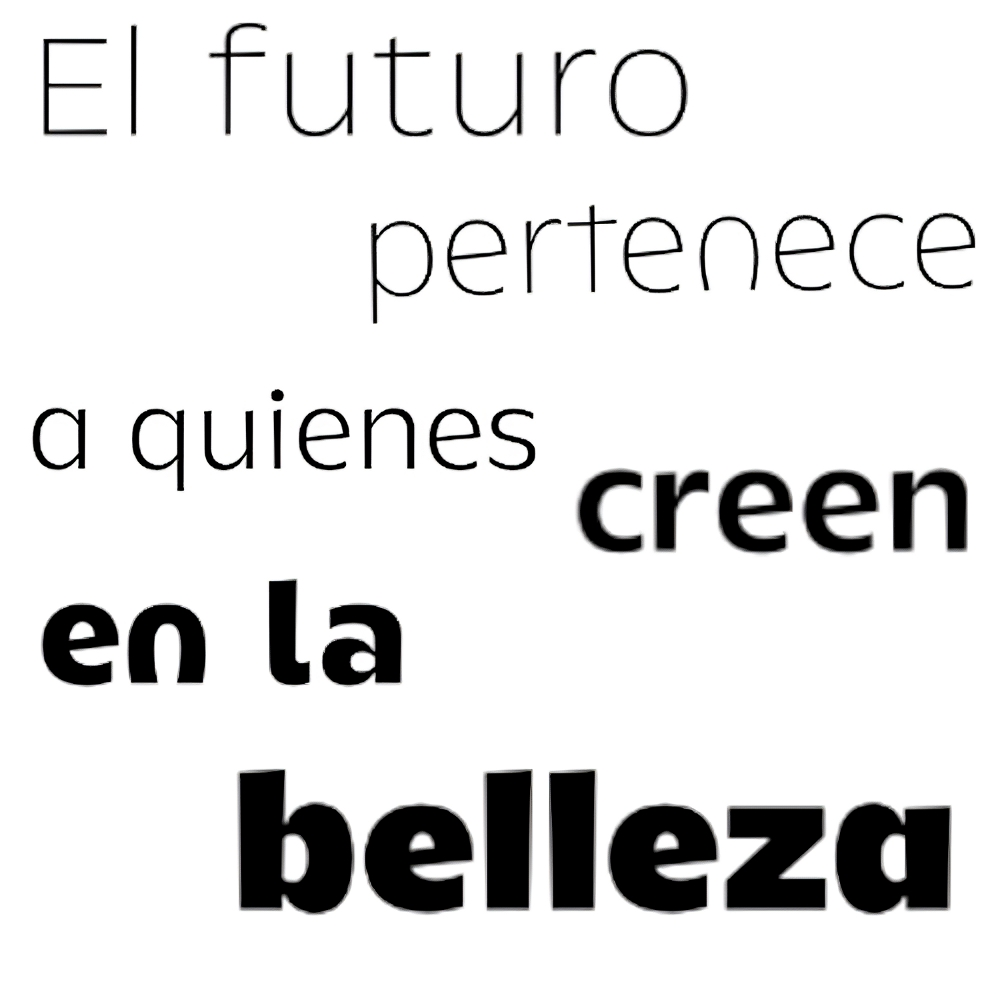
Kiara
| Año | 2023 |
| Créditos | Rodrigo Araya Salas, Bruno Jara Ahumada |
| Descripción | El tipo de letra Kiara es un tipo de letra diseñado para títulos informales con letras muy expresivas. Además, contiene más de 12 variantes |
| Familia(s) | Kiara Thin, Kiara Thin Alternative, Kiara Light, Kiara Light Alternative, Kiara Regular, Kiara Regular Alternative, Kiara Bold, Kiara Bold Alternative, Kiara Black, Kiara Black Alternative, Kiara Black Shadow, Kiara Black Alternative Shadow |
| Fundidora | RodrigoTypo |